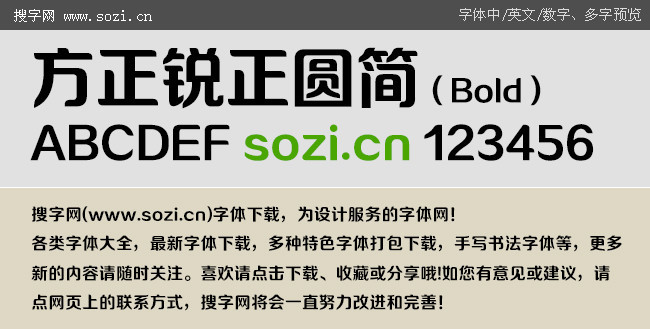
方正銳正圓簡Bold
搜字網(wǎng)提供一款方正銳正圓簡中文字體下載,銳正圓系列是銳正黑系列的擴(kuò)展與延伸,屬性介于圓體與黑體之間,是適度中和的中性設(shè)計(jì),既有圓體的圓潤,又不失黑體的厚硬,柔中帶銳、圓中有方。筆鋒采用半圓角設(shè)計(jì),相較黑體、圓體更具圓潤兼銳化的時(shí)尚度,而太過夸張時(shí)尚又有失莊重,故而有意做適度收斂,圓融時(shí)尚而又端莊穩(wěn)重,適用領(lǐng)域廣泛。